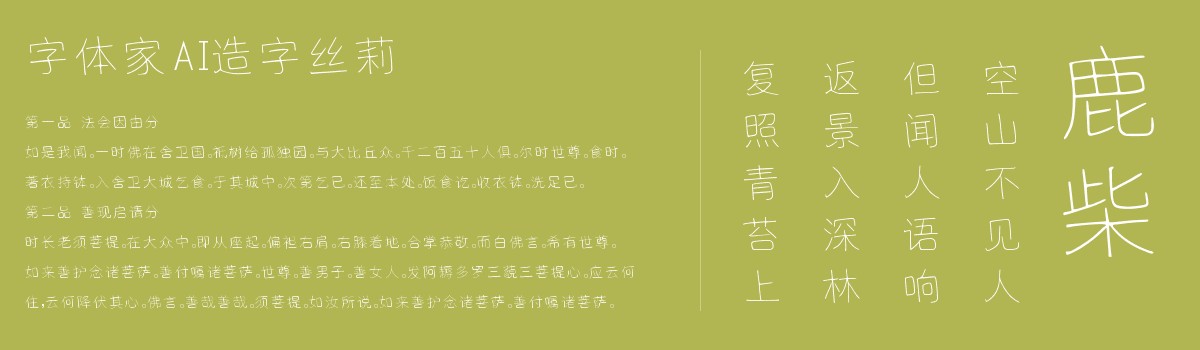
字体家AI造字丝莉
字体家AI造字丝莉这款字体整体透着柔婉细腻的气质。笔画圆润无锋,起笔收笔都带着自然的弧度,没有生硬的棱角。线条粗细有微妙变化,如蚕丝般轻盈,又似溪流般流畅,转折处柔和过渡,像叶片边缘的卷边。结构匀称舒展,每个笔画都像被细心梳理过,彼此呼应却不纠缠,重心平稳得像静置的湖面,透着一种温润、娴静的韵律感,摸上去该是光滑细腻,毫无滞涩的。适合用于一些广告标题、平面文案、海报标题、网页广告用字的编辑。